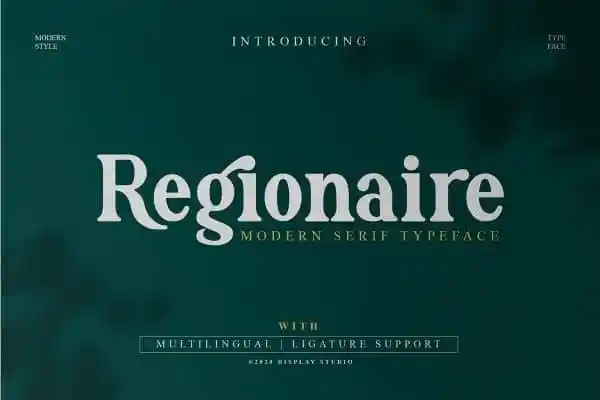
Regionaire Serif Font – Download Grátis
A Regionaire Serif Font é uma opção perfeita para quem busca uma mistura única e sofisticada entre a elegância tradicional dos serifos e a personalidade vintage. Com letras alternativas, swashes antigos e ligaturas únicas, esta fonte oferece recursos suficientes para transformar qualquer design em algo realmente único e verdadeiramente autêntico à sua marca. Com um aspecto forte que transmite elegância e confiabilidade, a Regionaire Serif traz ao seu projeto uma vibe vintage moderna. Além disso, o fato de suportar alternativas e ligaturas permite criar variedades interessantes entre versões leves e pesadas, proporcionando flexibilidade para adaptá-la à sua necessidade específica. Para quem está buscando adicionar um toque distintivo ao seu design gráfico, a Regionaire Serif é uma fonte ideal. Ela oferece uma combinação perfeita de elegância tradicional e personalização moderna que certamente impressionará seus clientes com a qualidade do trabalho.